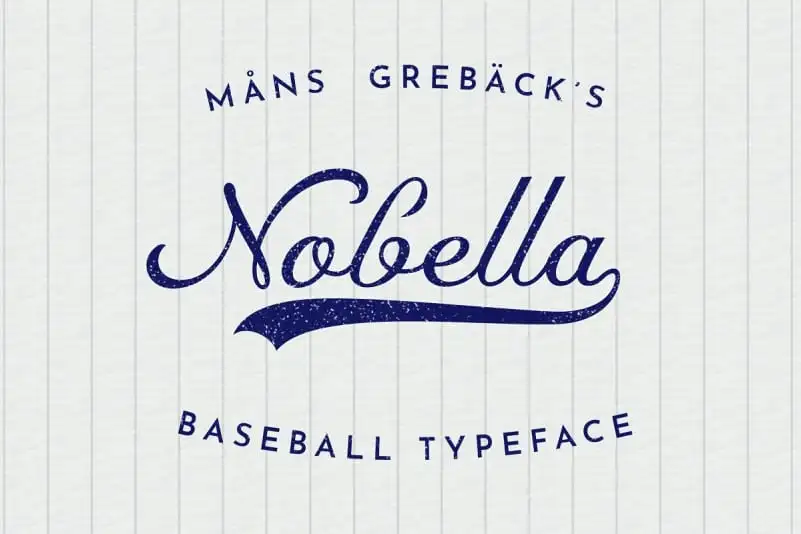
Nobella Calligraphy Font é uma elegante letra script que se destaca por sua curvilínea forma e detalhes decorativos. Ela foi criada pelo designer Mans Greback, conhecido por suas criações de alta qualidade. Este estilo único oferece um toque retro e sofisticado às logomarcas, garantindo-lhes um aspecto criativo e vibrante. Suas letras maiúsculas grandes e linhas finas conferem ao tipo uma textura leve e expressiva, tornando-o perfeito para aqueles que buscam dar seu design uma cara moderna e única. A Nobella Calligraphy é uma ótima escolha tanto para designers profissionais quanto para iniciantes no campo da gráfica, oferecendo uma fonte versátil e elegante capaz de enriquecer qualquer projeto de layout.